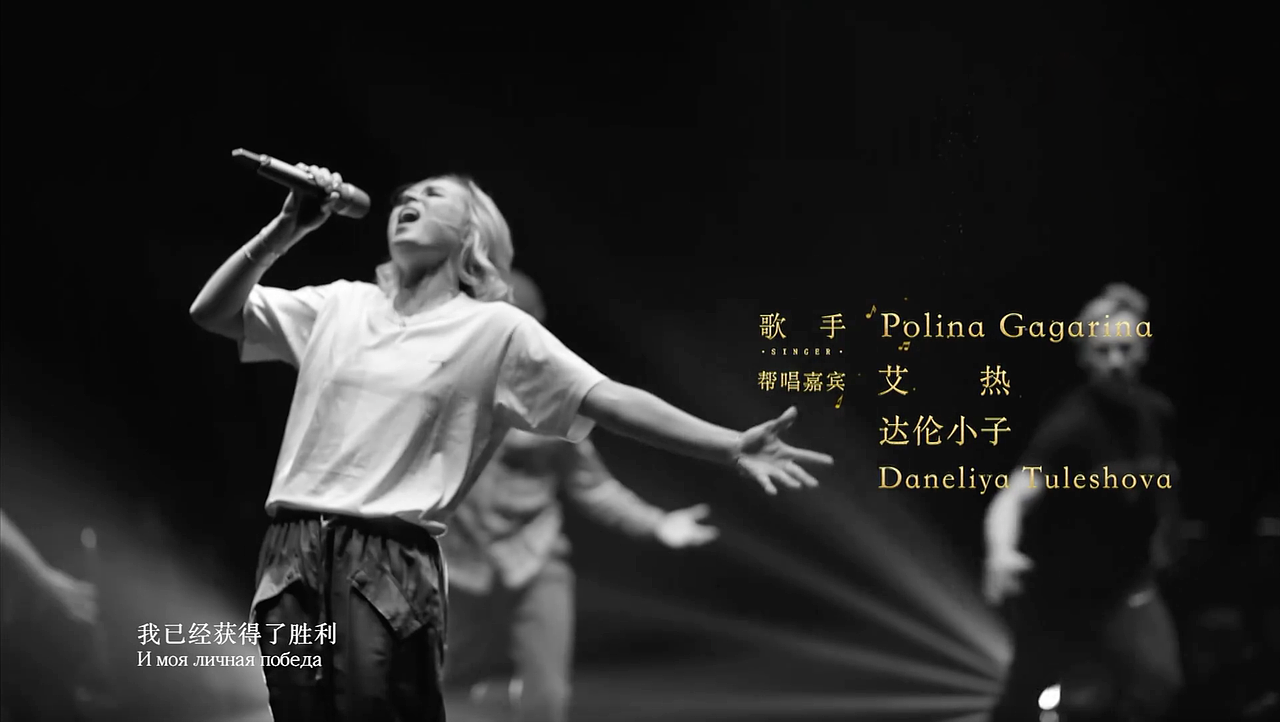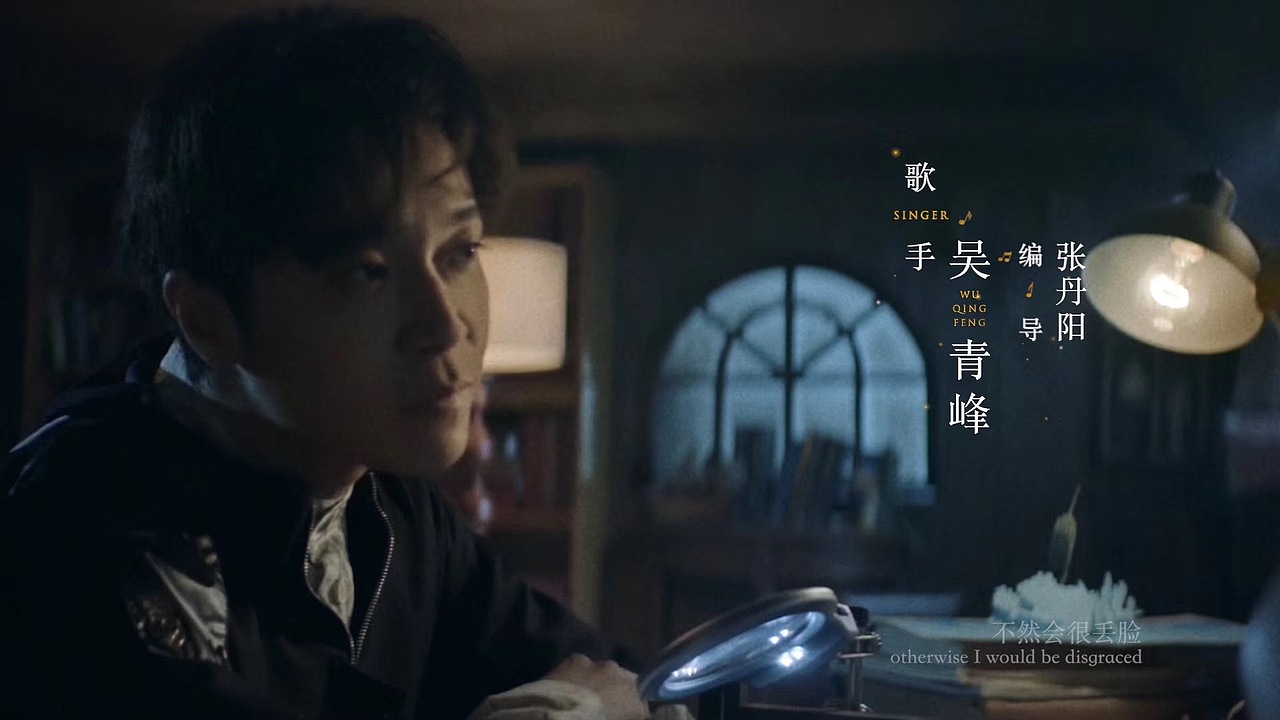
湖南卫视2019《歌手》片头平面
《歌手》结束有段时间了,来站酷发作品也相隔了蛮久,发现做完《歌手》片头平面还是挺骄傲的,还是得分享下。确实这季跟以往大不相同,电影片头叙事结构,画面感极简但不简单,所以当时的灵感浮现出——宋体。其实19年年初的时候节目组尝试过很多方法,都觉得没有创新,最终敲定了电影的质感,所以宋体就突围了。这样不抢画面又强调片头的功能性,让画面更加完善。最后一期应节目组要求稍微做了升级改变,添加了质感和小元素做下结尾区分。同时总决赛宣传片词也有所不同。(题外话:时隔这么久分享做品,都有点不好意思发,得好好整理下了!)